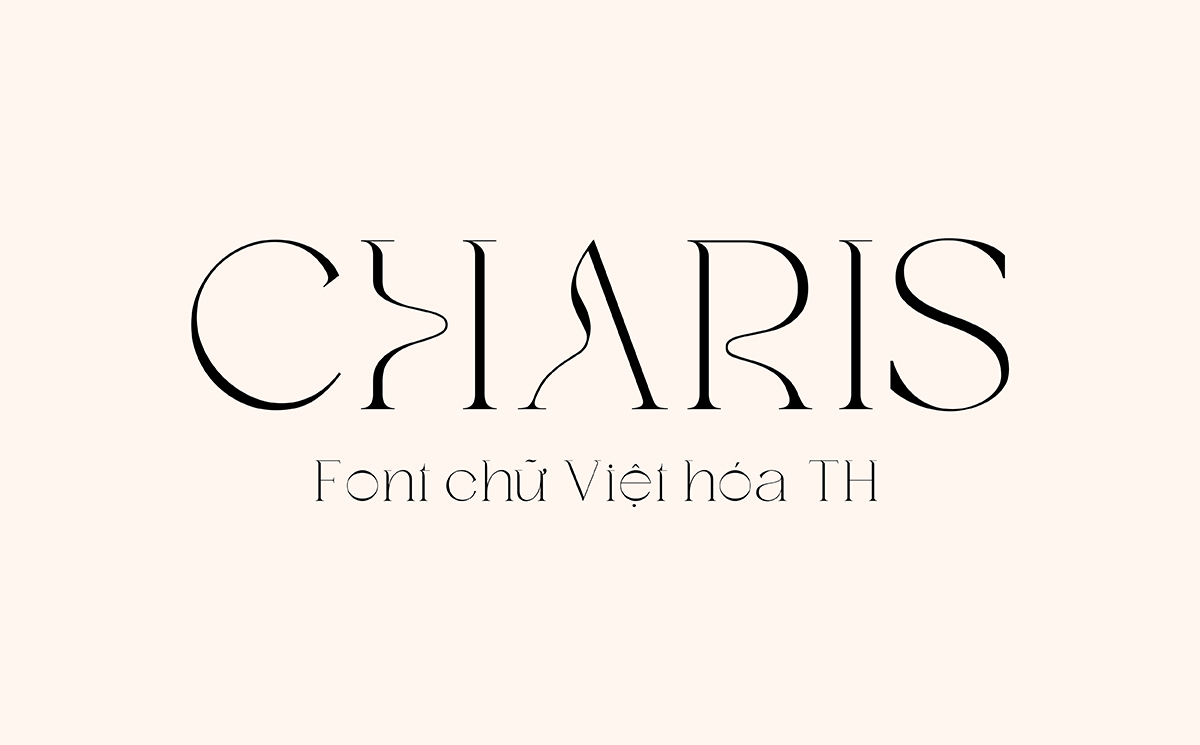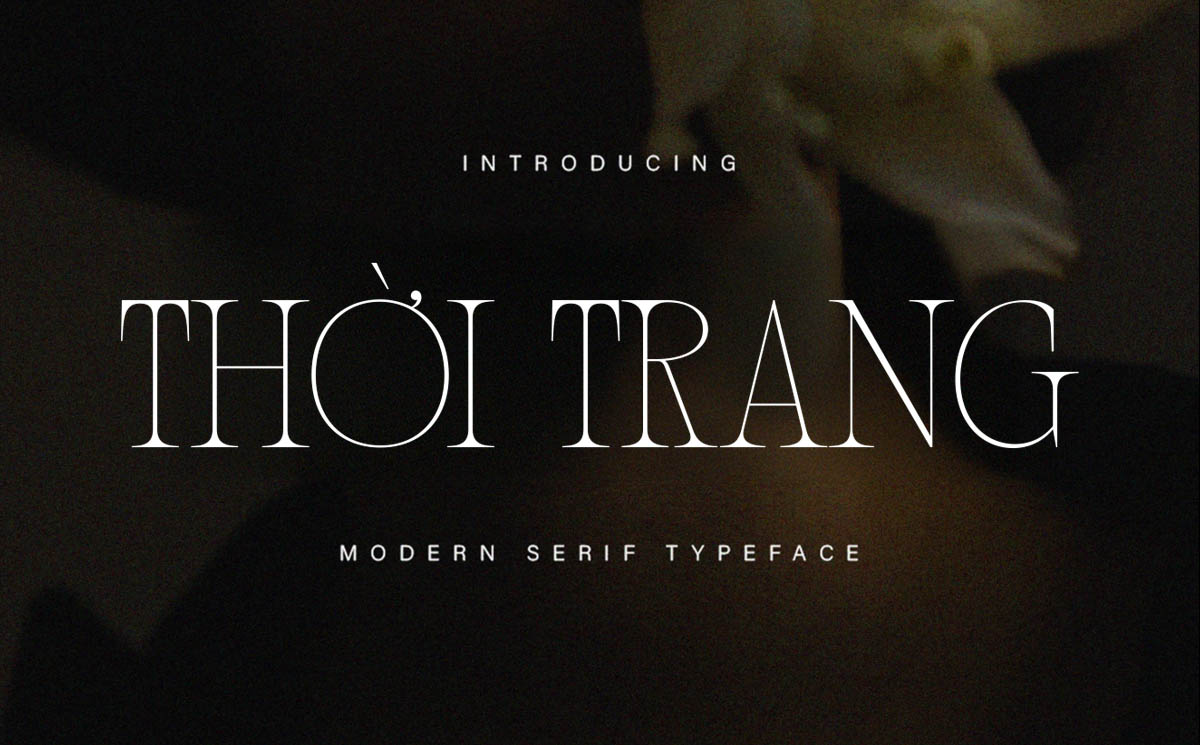
Font chữ cho catalog trang sức và phụ kiện cao cấp: tinh tế mà không khó đọc
Gợi ý font TH Việt hóa cho catalog trang sức, phụ kiện cao cấp, lookbook jewelry và bộ nhận diện luxury.
Catalog trang sức và phụ kiện cao cấp cần một hệ chữ rất tinh tế: đủ sang để nâng giá trị sản phẩm, nhưng không được quá cầu kỳ đến mức khách khó đọc tên bộ sưu tập, chất liệu, kích thước hoặc giá.
Với jewelry lookbook, font không chỉ làm đẹp trang bìa. Font còn xuất hiện ở caption ảnh, thông số sản phẩm, trang câu chuyện thương hiệu, thiệp mời, hộp quà, voucher và banner social. Vì vậy, nên chọn font TH Việt hóa có dấu tiếng Việt rõ, tỷ lệ chữ thanh thoát và dễ phối cùng ảnh sản phẩm.
Cách chọn font cho catalog trang sức cao cấp
Nếu catalog có nhiều ảnh close-up nhẫn, dây chuyền, đá quý hoặc đồng hồ, hãy ưu tiên serif thanh lịch cho tiêu đề và một font phụ rõ ràng cho phần mô tả. Font quá mảnh có thể đẹp ở khổ lớn nhưng dễ mất nét khi in nhỏ, đặc biệt ở dấu tiếng Việt.
Với bìa catalog, tên collection và quote thương hiệu, bạn có thể dùng font luxury nổi bật hơn. Với bảng thông số như chất liệu, mã sản phẩm, kích thước, bảo hành và giá, hãy giữ chữ đơn giản, khoảng cách dòng thoáng và độ tương phản cao.
Gợi ý font TH Việt hóa cho catalog trang sức và phụ kiện cao cấp
Danh sách dưới đây ưu tiên các font TH có tinh thần luxury, serif, thanh lịch và dễ dùng trong ấn phẩm catalog. Mỗi font có ảnh preview và link tải để bạn test nhanh với tên thương hiệu thật.
1. TH Vintoria
TH Vintoria phù hợp với phong cách hoàng gia, hợp bìa catalog trang sức cổ điển, logo phụ và tiêu đề bộ sưu tập có tinh thần heritage. Khi dùng trong catalog trang sức, hãy đặt font ở vai trò tiêu đề, tên collection, trang mở đầu hoặc điểm nhấn thương hiệu. Phần mô tả sản phẩm nên phối với font phụ rõ hơn để khách đọc nhanh trên bản in lẫn màn hình.
2. TH Selvia Genatu
TH Selvia Genatu phù hợp với serif sang trọng, hợp catalog nhẫn cưới, vòng cổ, phụ kiện premium và các layout nhiều khoảng trắng. Khi dùng trong catalog trang sức, hãy đặt font ở vai trò tiêu đề, tên collection, trang mở đầu hoặc điểm nhấn thương hiệu. Phần mô tả sản phẩm nên phối với font phụ rõ hơn để khách đọc nhanh trên bản in lẫn màn hình.
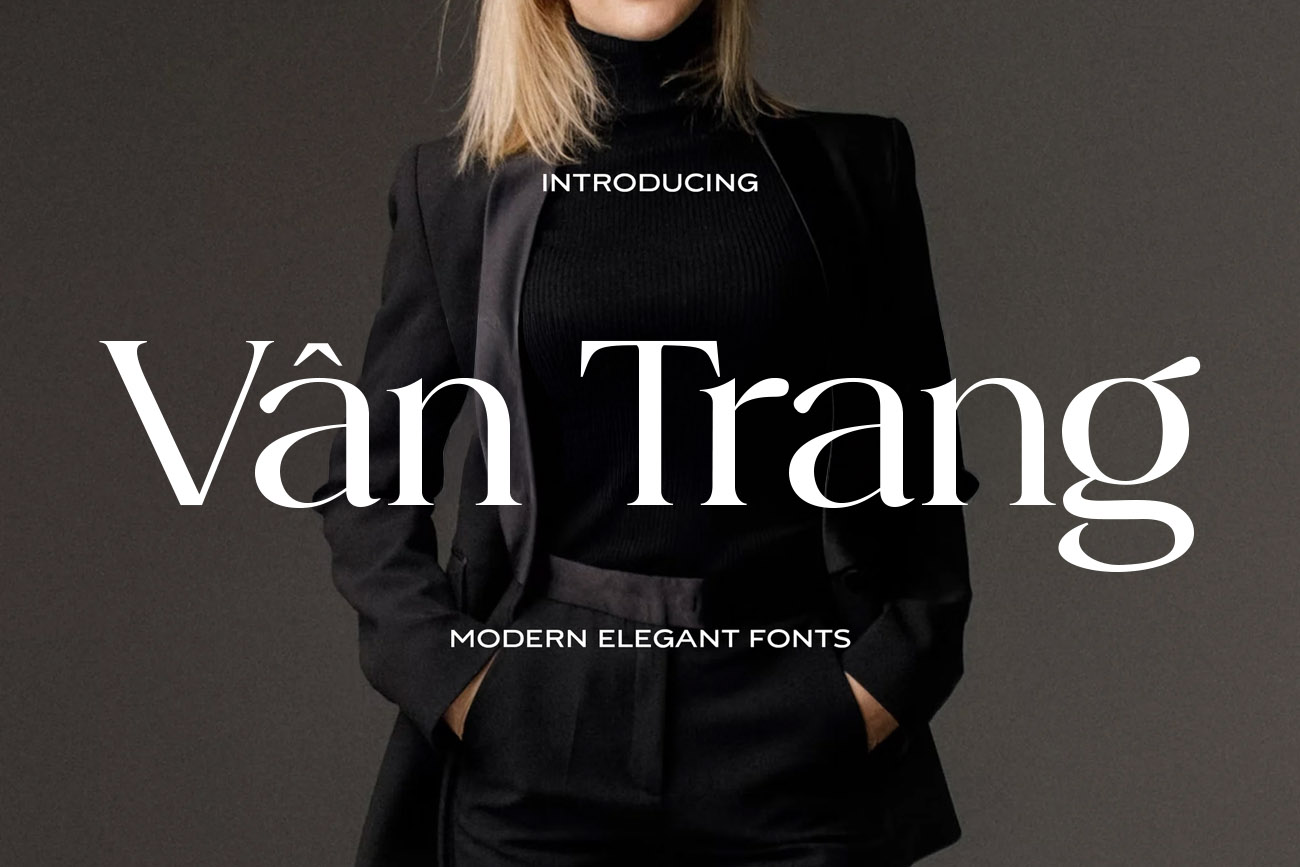
3. TH Top Luxury
TH Top Luxury phù hợp với dáng luxury rõ, hợp headline trang mở đầu, poster ra mắt collection và quote thương hiệu. Khi dùng trong catalog trang sức, hãy đặt font ở vai trò tiêu đề, tên collection, trang mở đầu hoặc điểm nhấn thương hiệu. Phần mô tả sản phẩm nên phối với font phụ rõ hơn để khách đọc nhanh trên bản in lẫn màn hình.
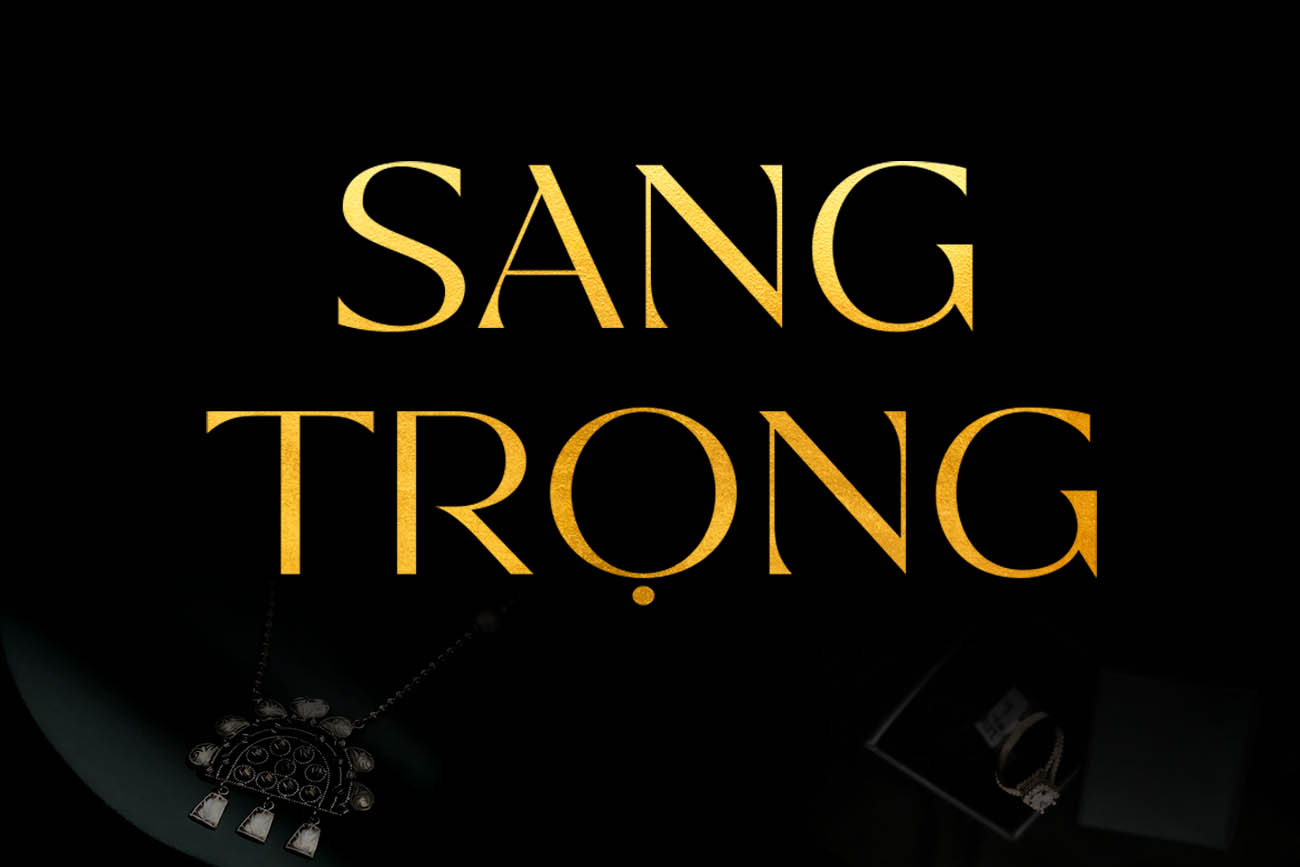
4. TH Luxury 5
TH Luxury 5 phù hợp với serif nét mảnh, hợp catalog trang sức nữ, phụ kiện thanh lịch và thiết kế cần cảm giác nhẹ. Khi dùng trong catalog trang sức, hãy đặt font ở vai trò tiêu đề, tên collection, trang mở đầu hoặc điểm nhấn thương hiệu. Phần mô tả sản phẩm nên phối với font phụ rõ hơn để khách đọc nhanh trên bản in lẫn màn hình.
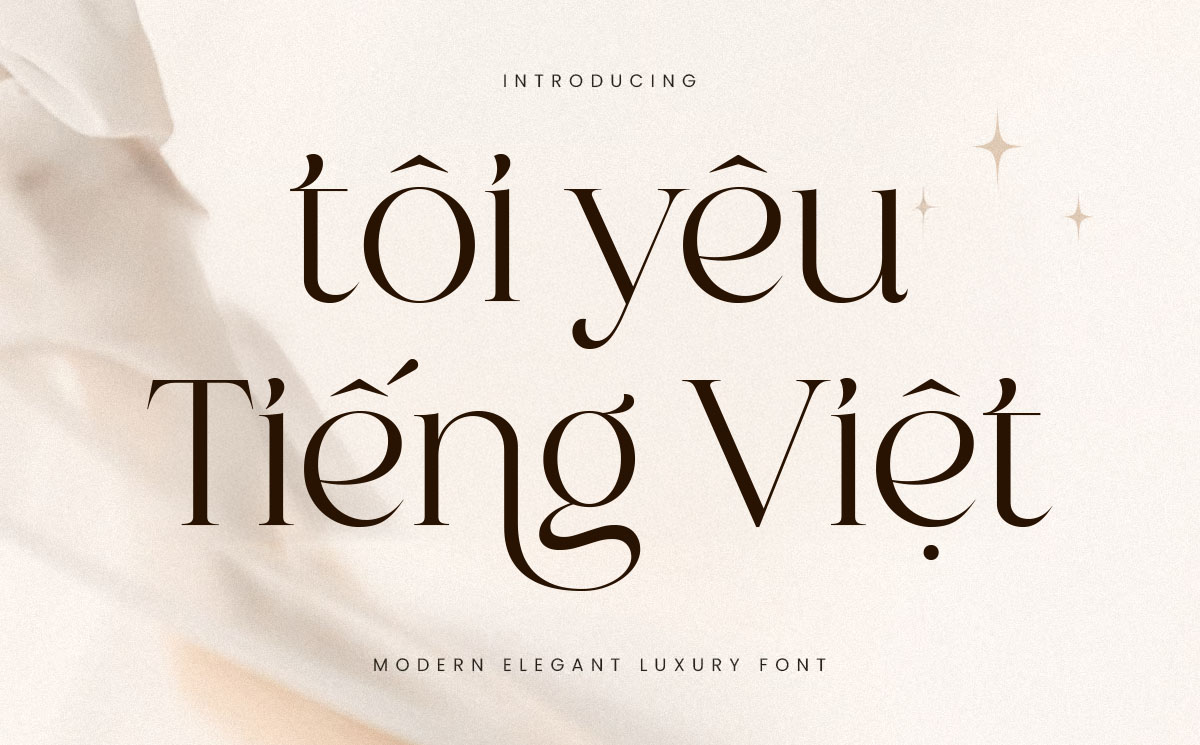
5. TH Luxury 7
TH Luxury 7 phù hợp với serif sang trọng, phù hợp tiêu đề bộ sưu tập, brochure thương hiệu và layout in ấn cao cấp. Khi dùng trong catalog trang sức, hãy đặt font ở vai trò tiêu đề, tên collection, trang mở đầu hoặc điểm nhấn thương hiệu. Phần mô tả sản phẩm nên phối với font phụ rõ hơn để khách đọc nhanh trên bản in lẫn màn hình.
6. TH Bevas
TH Bevas phù hợp với luxury hiện đại, hợp phụ kiện thời trang, đồng hồ, túi xách nhỏ và các campaign social premium. Khi dùng trong catalog trang sức, hãy đặt font ở vai trò tiêu đề, tên collection, trang mở đầu hoặc điểm nhấn thương hiệu. Phần mô tả sản phẩm nên phối với font phụ rõ hơn để khách đọc nhanh trên bản in lẫn màn hình.
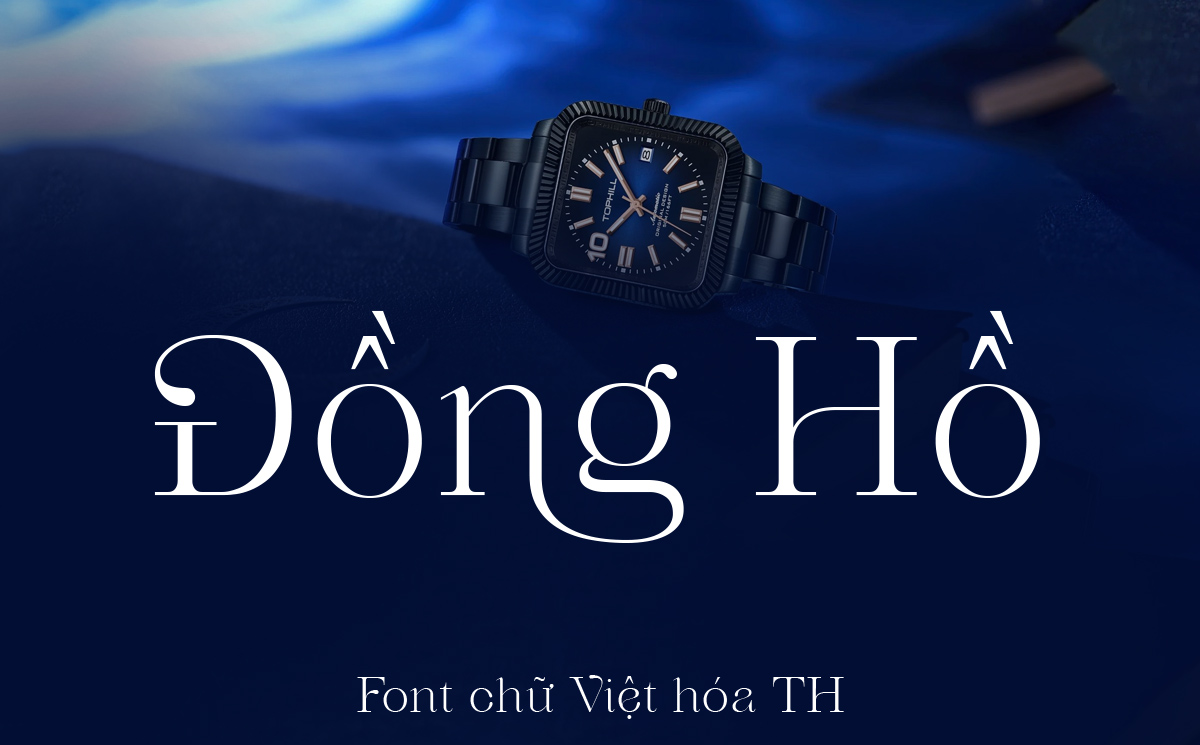
7. TH Runalto
TH Runalto phù hợp với cân bằng giữa sang trọng và dễ đọc, dùng tốt cho tiêu đề trang trong catalog hoặc tên nhóm sản phẩm. Khi dùng trong catalog trang sức, hãy đặt font ở vai trò tiêu đề, tên collection, trang mở đầu hoặc điểm nhấn thương hiệu. Phần mô tả sản phẩm nên phối với font phụ rõ hơn để khách đọc nhanh trên bản in lẫn màn hình.
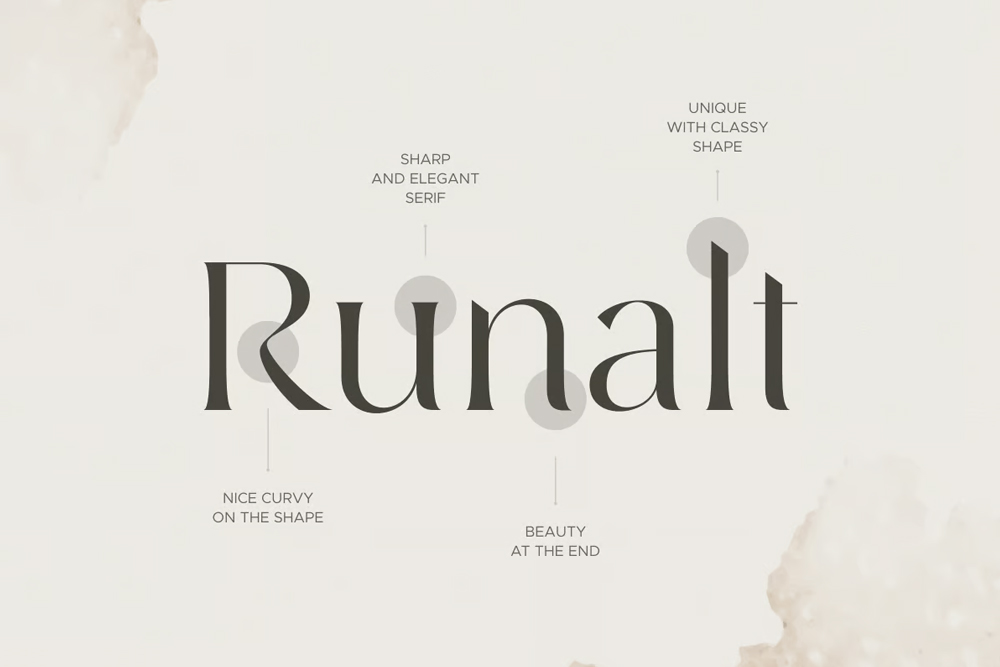
8. TH Castio
TH Castio phù hợp với cổ điển, hợp catalog vàng, đá quý, đồng hồ cổ điển và nhãn hộp quà cao cấp. Khi dùng trong catalog trang sức, hãy đặt font ở vai trò tiêu đề, tên collection, trang mở đầu hoặc điểm nhấn thương hiệu. Phần mô tả sản phẩm nên phối với font phụ rõ hơn để khách đọc nhanh trên bản in lẫn màn hình.
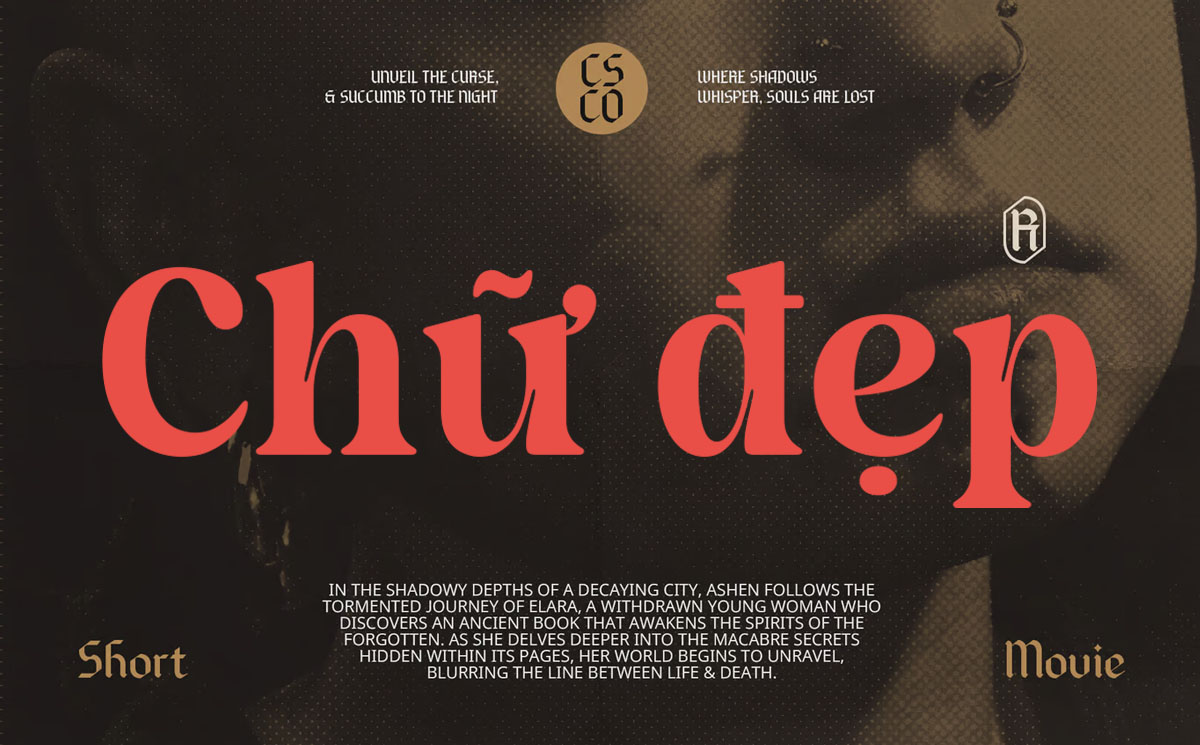
9. TH Hustle Culture
Font catalog trang sức nên tạo cảm giác tinh tế, cao cấp và đáng tin, nhưng vẫn phải hỗ trợ khách đọc thông tin sản phẩm thật nhanh. Bạn có thể bắt đầu với TH Selvia Genatu, TH Luxury 5, TH Waking, TH VADOLA, TH Charis Moderne hoặc TH Vintoria, sau đó test trên layout catalog thật trước khi triển khai toàn bộ bộ nhận diện.